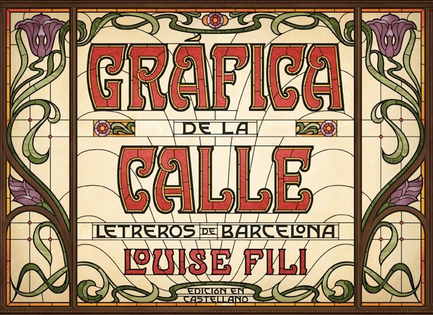
Las ciudades son seres vivos. Podemos ver cómo crecen, se desarrollan y, en algunos casos, pierden su pujanza hasta desaparecer o quedar atrapadas en un cierto limbo temporal ajenas al devenir de la historia.
También nos hablan nos susurran y nos gritan y esto lo hacen a través de rótulos comerciales, señales o anuncios de todo tipo.
Y, por lo general, estas “voces” nos devuelven un retrato fidedigno del carácter de una ciudad y nos sugiere un delicado hilo conductor que recorre su historia.
Esta arqueología urbana se ha visto reflejado en numerosos títulos publicados sobre diferentes ciudades a lo largo y ancho del planeta.
Por supuesto, Barcelona es una de ellas y sobre esta ciudad y su registro tipográfico trata el libro que hoy os presento.
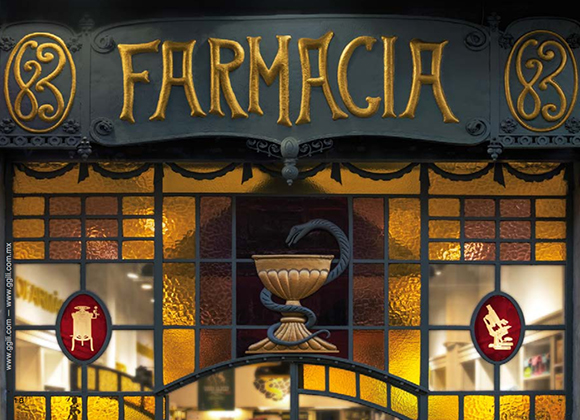
Se trata de Gráfica de la calle. Letreros de Barcelona y está escrito, mejor dicho fotografiado, por la diseñadora gráfica Louise Fili. En sus páginas nos encontramos con el rastro de esa Barcelona decimonónica y modernista, la Barcelona que Eduardo Mendoza reflejó en su novela La ciudad de los prodigios, y que se plasma en azulejos, vidrieras o mosaicos que presentan los delicados y orgánicos trazos art nouveau en sus letras.
También nos asaltan retazos de otra Barcelona cosmopolita, atenta a los movimientos vanguardistas que se extendieron por Europa durante el primer tercio del siglo XX y que dejaron su impronta en rótulos comerciales y en fachadas de edificios.
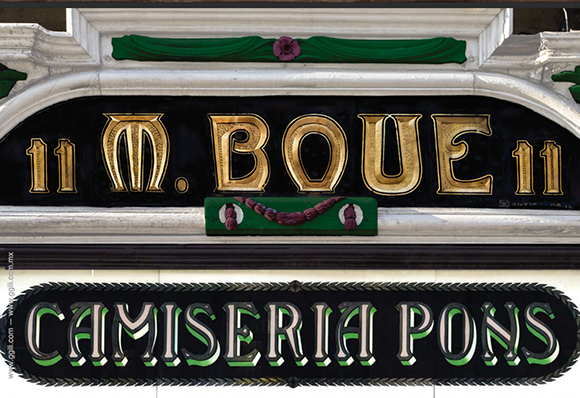
La Barcelona fabril, vecinal, en los reclamos de los “botiguers” que llenan los barrios de la ciudad con sus humildes reclamos que solicitan nuestra atención práctica y directa pero que no renuncian a mostrar su lado artístico, la Barcelona industrial y sus poderosos altavoces tipográficos, la Barcelona condal y aristócrata vestida con refinados trazos y contenidas y mayestáticas expresiones gráficas.
El libro está dividido en varias secciones que van desde el modernismo y el art nouveau, que ocupan la parte más importante del libro, a detalles integrados en edificios, monogramas o mosaicos y vitrales.
La calidad de las fotografías es muy buena y su formato y puesta en página facilita la inmersión en los detalles de las mismas haciendo de la lectura visual del volumen una experiencia placentera.
Un buen título para explorar un sujeto muy interesante. En este caso la Barcelona gráfica.